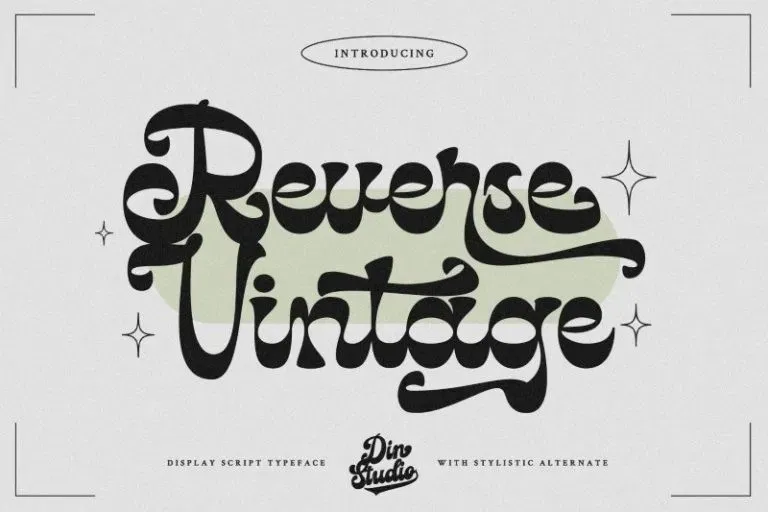
Reverse Vintage Font – Download Grátis
A fonte Reverse Vintage é uma escolha perfeita para qualquer projeto que deseja capturar a essência vintage com estilo moderno e descontraído. Especificamente projetada para se adaptar a um vasto espectro de necessidades de conteúdo e projetos, esta fonte traz um toque romântico ao mesmo tempo em sua dinâmica presença. O Reverse Vintage foi meticulosamente pensado para facilmente mesclar dentro dos teus designs. Seu traço curvoso é uma excelente base, permitindo-te moldar a tua ideia. Adapta os teus lemas de opulência e luxo com esta fonte elegante e apresenta as tuas letras cursivas em qualquer projeto, deixando o seu público completamente surpresos e impactados por ela.